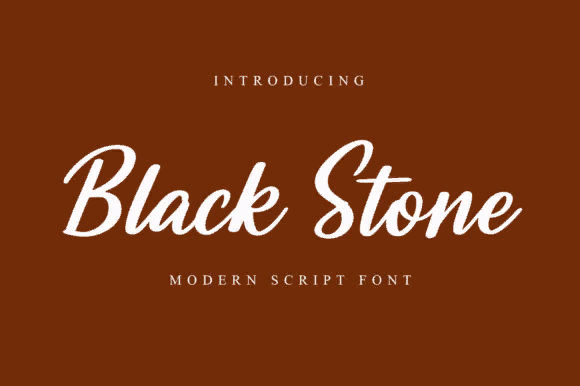
Название: Black Stone Font (2021)
Black Stone - это уникальный и элегантный рукописный шрифт.
Он прекрасно смотрится на различных дизайнах, требующих индивидуального стиля, таких как свадебные приглашения, благодарственные открытки, свадьбы, поздравительные открытки, логотипы и так далее.
Название: Black Stone Font (2021)
Black Stone - это уникальный и элегантный рукописный шрифт.
Он прекрасно смотрится на различных дизайнах, требующих индивидуального стиля, таких как свадебные приглашения, благодарственные открытки, свадьбы, поздравительные открытки, логотипы и так далее.